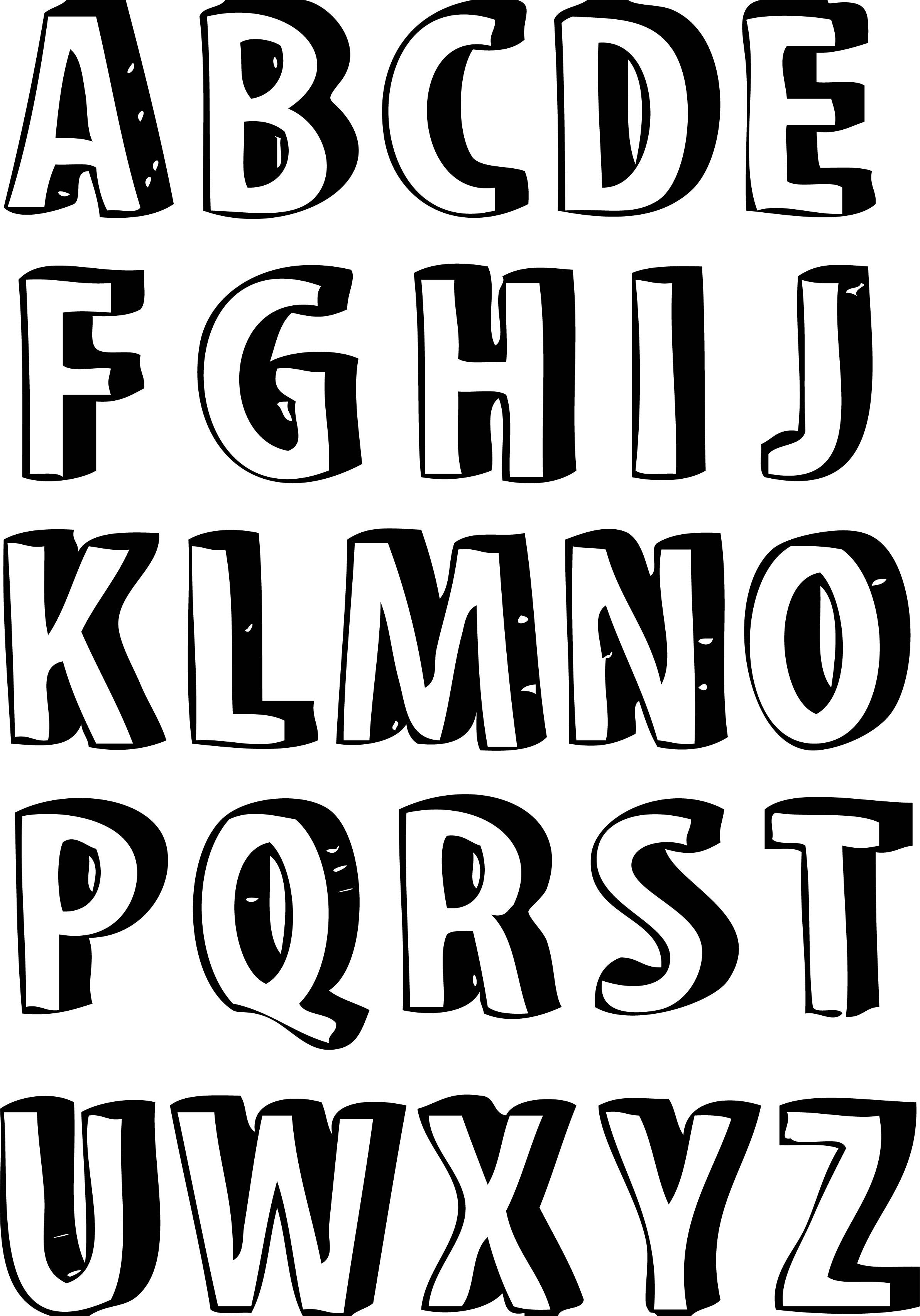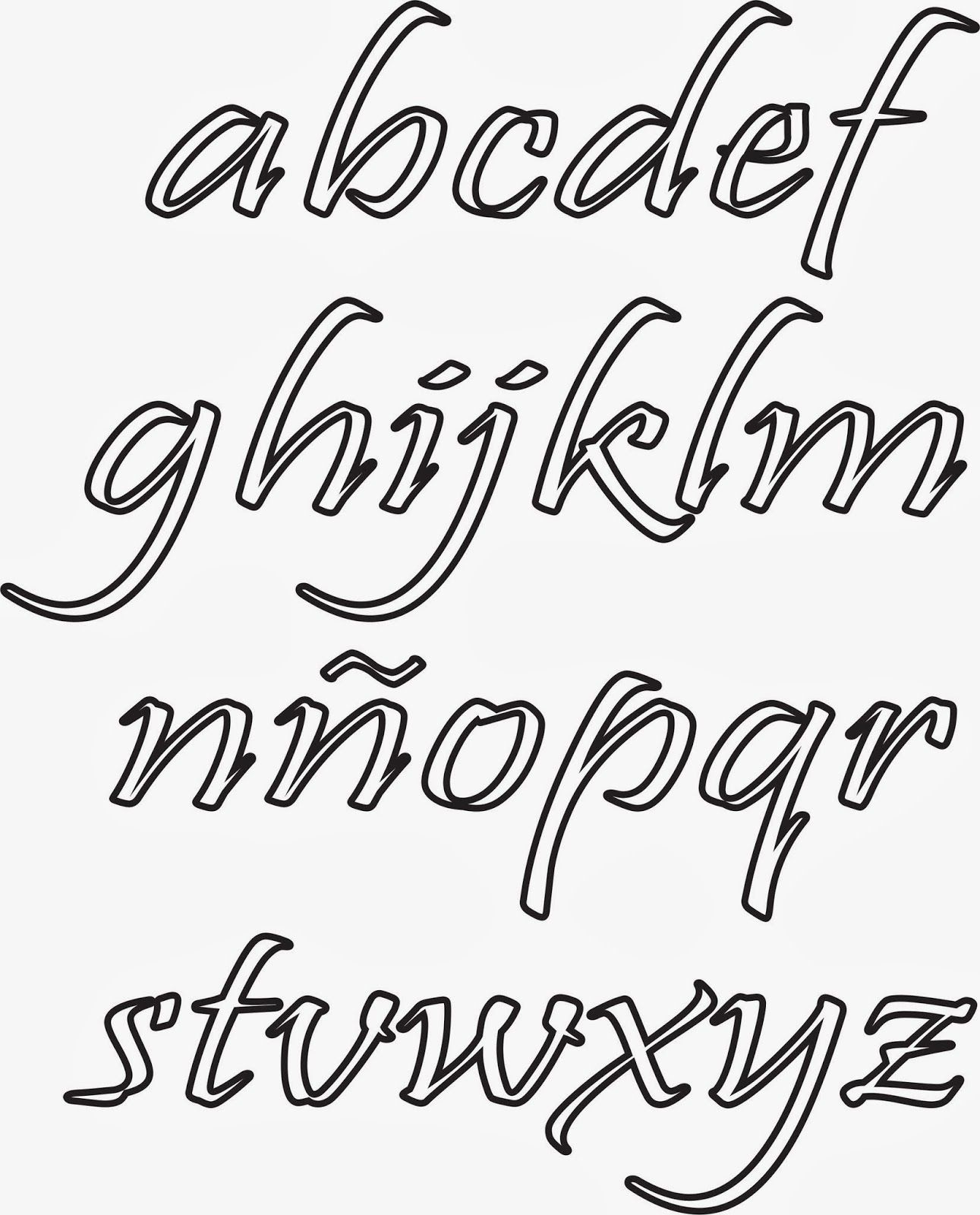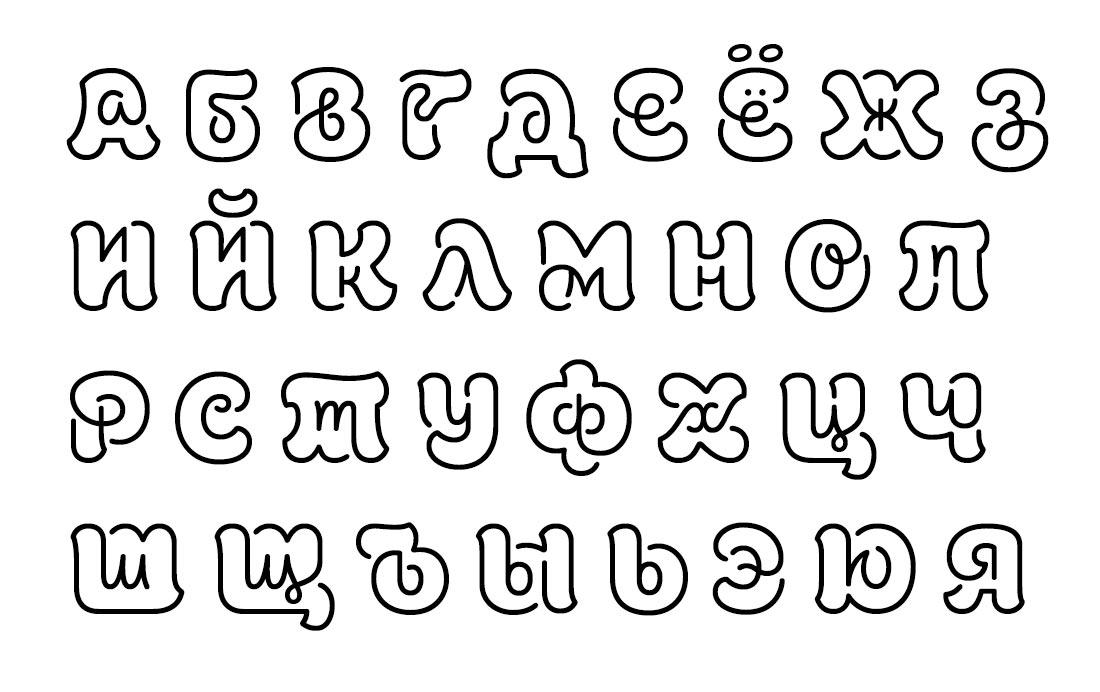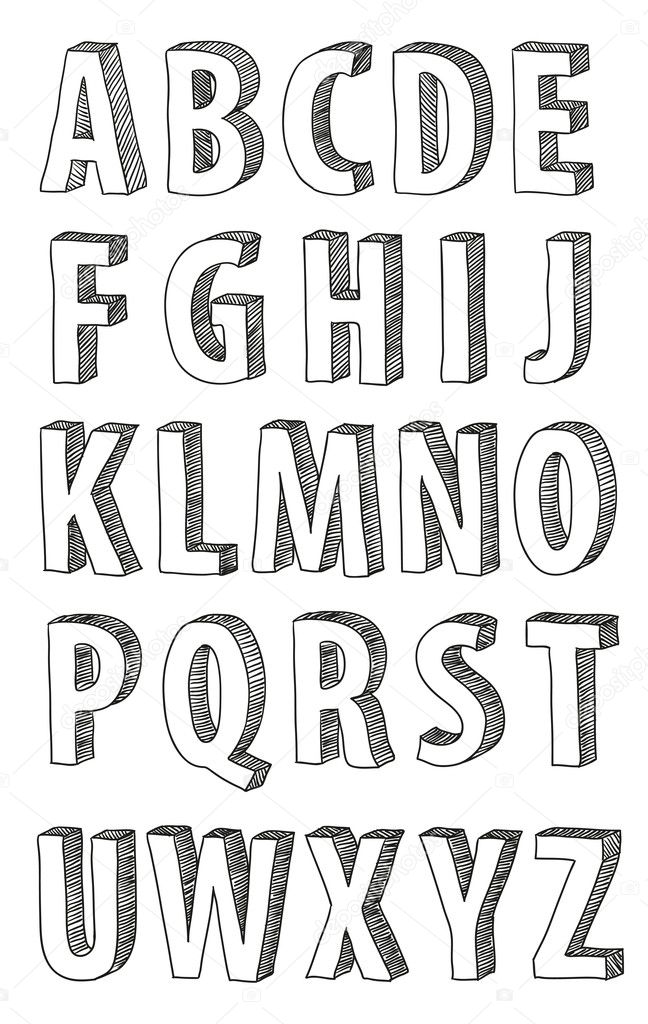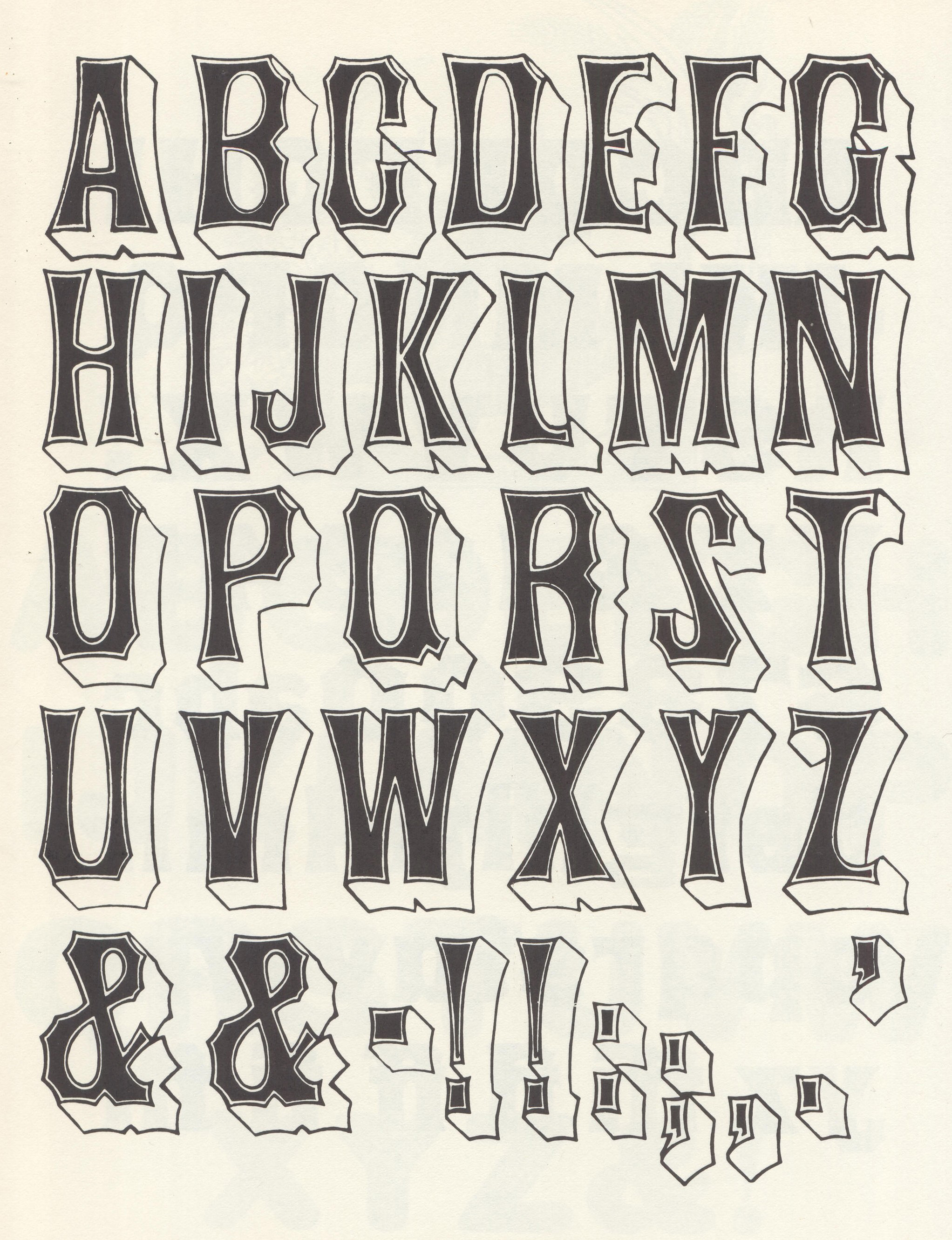
Шрифты для рисования: Надписи, Декоративные шрифты, Шрифт алфавит
Шрифты “от руки”: учимся рисовать
В эпоху социальных сетей и смартфонов в скором времени в обществе станут появляться люди, которые лишь понаслышке будут знать, что такое письма от руки. Меньше всего в современном мире человек при желании общаться с родными и близкими заботится теперь о написании бумажных писем.
Проще и быстрее отправить короткое текстовое или звуковое сообщение, но что если вам захочется выразить свои чувства при помощи писем от руки?
Как воспользоваться рукописным текстом, какие рукописные шрифты бывают и где их найти, об этом поговорим в сегодняшнем посте. Единственное, что мы можем сказать с полной уверенностью, даже непрофессионал и человек далекий от понимания каллиграфии сможет воспользоваться приведенными ниже примерами, чтобы создать красивое, яркое и незабываемое письмо.
Начнем с пошагового плана. И для начала выберем несколько интересных шрифтов, которые будем использовать при создании письма. Ну и вспомним о популярных трендах в типографике.
Всему нужна основа
Прежде всего вам необходимо набросать структуру своих будущих писем. Одна из самых распространенных ошибок — игнорирование начальных шагов, спешка и жгучее желание добиться результата как можно быстрее. Ваше письмо и в целом стиль рукописного ввода будут выглядеть привлекательнее, если сначала создать скелет.
После подготовки основы для будущего рукописного сообщения можно переходить к буквам. Здесь также не стоит торопиться, тщательно прорисованный элемент требует усердия и времени.
Дальше можно оживить буквы и слова элементами выбранного шрифта. Не бойтесь экспериментировать с кривыми и плавными линиями и т.д.
Предлагаем ознакомиться с предложенными ниже видео, чтобы научиться каллиграфии.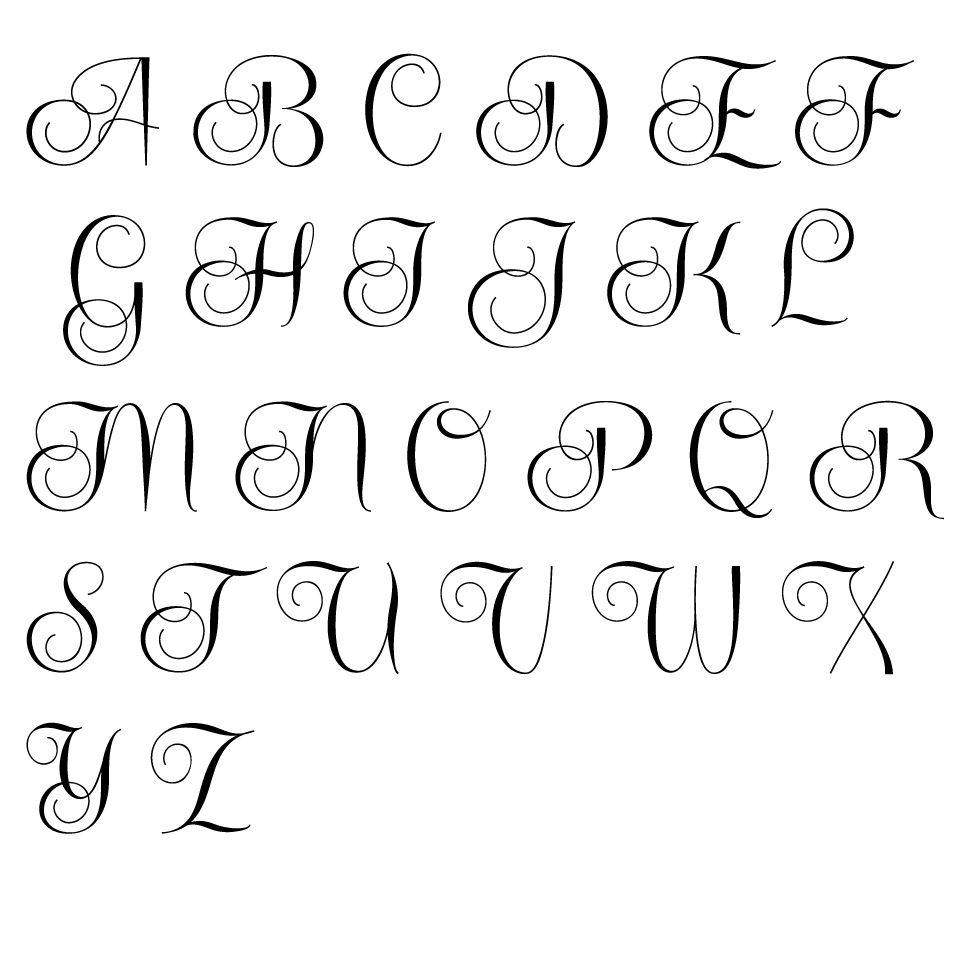
Как научиться современной каллиграфии. Пособие для новичков
Как писать каллиграфическим почерком
Сценарий каллиграфии для начинающих — бесплатные рабочие таблицы!
Кисти для письма — 8 основных штрихов для каллиграфии
Если вы не хотите изучать каллиграфию самостоятельно, но хотите использовать красивые рукописные шрифты на своем сайте, воспользуйтесь уже готовыми наборами шрифтов. Мы подготовили подборку из 15 лучших рукописных шрифтов от TemplateMonster.
ТОП-15 рукописных шрифтов 2019
Рисование шрифта — презентация онлайн
1. Рисование шрифта
2. Шрифт может быть нарисован с применением чертежных инструментов или без них. Шрифт нарисованный «от руки»отличается более выраженным инд
Шрифт может быть нарисован сприменением чертежных
инструментов или без них.
Шрифт нарисованный «от
руки»отличается более
выраженным индивидуальным
характером
3.
Орудия рисования шрифта• Карандаш средней твердости. Для мелкогошрифта- более твердый.
• Резинка- мягкая.
• Линейка- 2 разные. Для карандаша- тонкая и
прозрачная ( видно часть рисунка под ней).
Для туши – деревянная, металлическая с
косым срезом внутрь- исключает затекание
туши.
• Треугольник- прозрачный
• Рейсфедер-2 шт. для толстых линий и для
тонких (более длинные и острые щечки)
Рейсфедер подтачивают на мелкозернистом
Персонажи
Эта идея от Dribble такая милая! Добавление символов к вашим персонажам — это забавный и причудливый способ оживить ваш текст.
Шрифт Cool S
Этот стиль уникален и остроконечен. Попробуйте добавить несколько точек и граней к своим символам, чтобы создать шрифт в стиле шестиугольника. Этот шрифт, несомненно, придаст вам современную и футуристическую эстетику.
Граффити
Классическим шрифтом для рисования является надпись в стиле граффити. Вы никогда не ошибетесь с надписями в стиле граффити, особенно если вы ищете уличную атмосферу.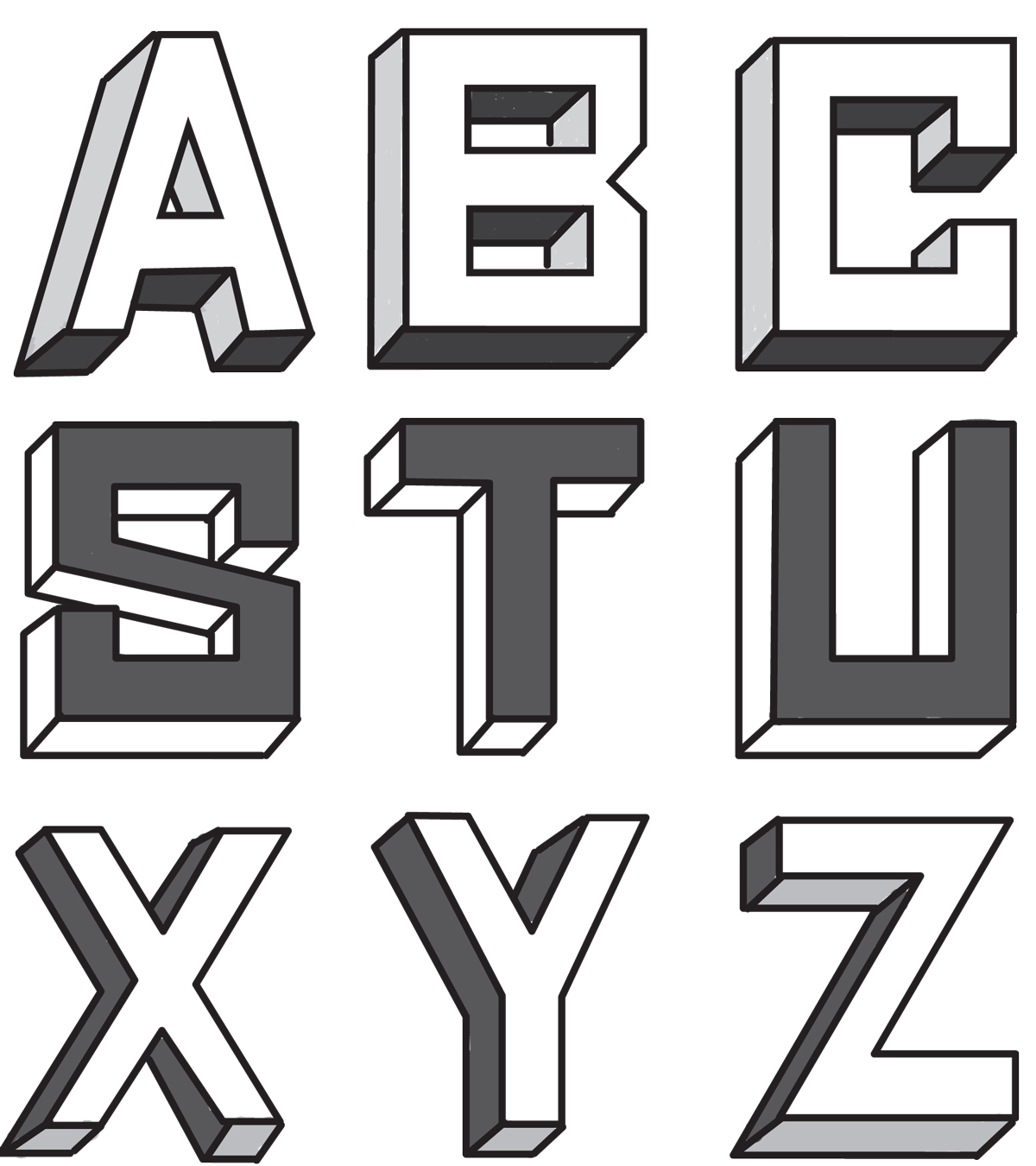